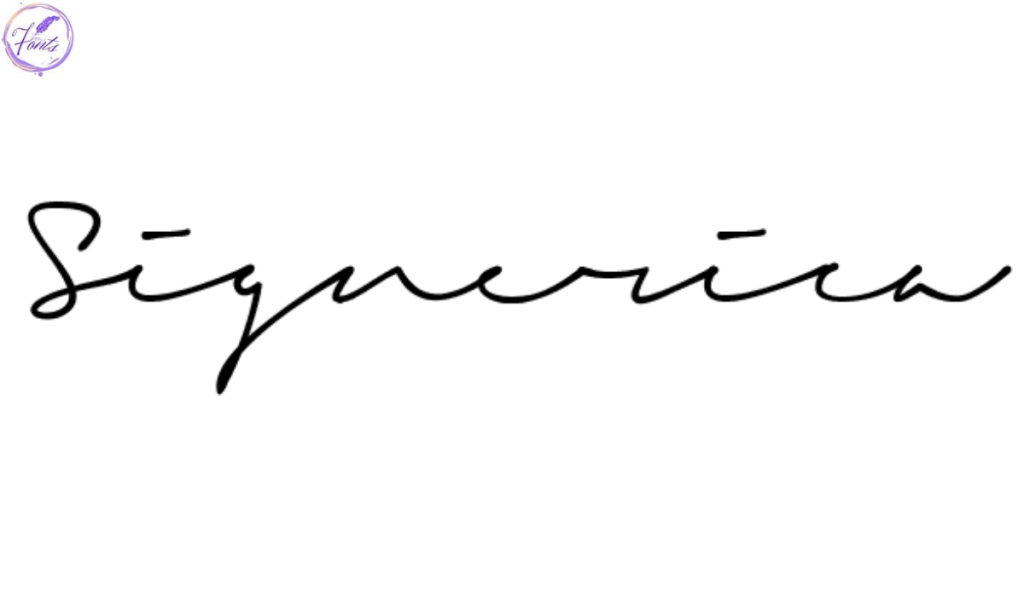
Font signerica việt hóa
Tác giả: Mans Greback
Ngày phát hành: 2011
Ngôn ngữ: Tiếng Việt, Tiếng Anh, và nhiều ngôn ngữ khác
Bộ Font: Signerica
Phân loại: cá tính, độc đáo, viết tay
Kiểu chữ: script
font signerica là một bộ font độc đáo và sáng tạo, được thiết kế bởiMans Greback vào năm 2011. Font này mang phong cách hiện đại, với các đường nét tinh tế và mạnh mẽ, giúp bạn tạo ra những thiết kế ấn tượng và thu hút.